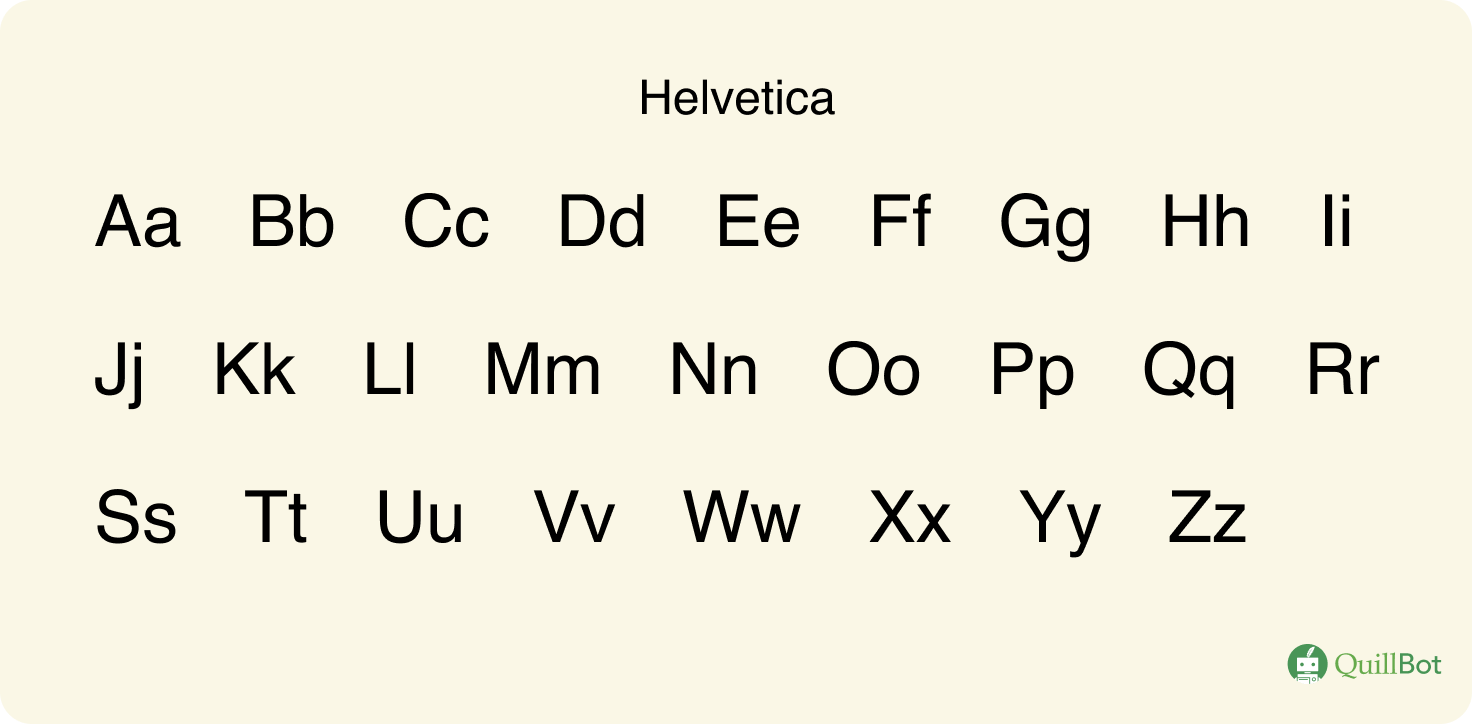
Helvetica | Une police intemporelle
Que ce soit sur le web, sur un panneau publicitaire, sur un bandeau télévisuel ou dans un magazine, le choix d’une police de caractère n’est jamais le fruit du hasard.
Loin de relever de la simple coquetterie ou du détail, une typographie peut, selon ses caractéristiques visuelles et l’ambiance qu’elle dégage, influencer considérablement la lisibilité et l’accessibilité d’un message, et même appuyer la ligne éditoriale d’une marque.
De polices, il en existe de toutes sortes : fines ou épaisses, fantaisistes ou classiques, rondes ou linéaires… L’offre, en vérité, est aujourd’hui pléthorique.
Parmi elles, on retrouve notamment les incontournables du genre, intégrés d’office sur tous les logiciels de traitement de texte par défaut, ou presque.
C’est à cette catégorie plus select qu’elle n’y paraît qu’Helvetica appartient.
- Année de création : 1957
- Pays de création : Suisse
- Créateur : Max Miedinger
- Type de police : Linéale
- Type d’empattement : Sans empattement (sans serif en anglais)
- Classification VoxAtypi : Linéale néo-grotesque
- Popularité : +++ (encore très populaire malgré son grand âge)
- Image véhiculée : Fonctionnelle, claire, universelle, mais aussi peu originale, voire austère.
- Point d’attention particulier : Espacement particulièrement serré (n’est donc pas adapté à tous les supports de lecture).
Helvetica, au même titre qu’Arial ou Times New Roman, figure parmi les polices les plus célèbres et influentes ; un incontournable dans l’univers du design graphique.
Le grand public, même lorsqu’il ne connaît pas son nom, a forcément déjà eu affaire à Helvetica.
Mais quels sont les secrets de cette popularité qui en fait toujours l’une des typographies les plus utilisées à l’échelle du globe actuellement ?
Comment est née la police Helvetica ?
La naissance d’Helvetica remonte à 1957.
On la doit à Max Miedinger, un spécialiste suisse de la création de caractères. Sous la houlette d’Eduard Hoffmann, celui-ci avait pour consigne de créer une police qui soit la plus neutre, pratique, rationnelle et universelle possible.
L’idée directrice était la suivante : cette nouvelle typographie devait laisser s’exprimer le texte en soi, sans orienter le lecteur quant à son contenu en raison de ses lignes et de son apparence.
Qu’à cela ne tienne : Miedinger s’est mis au travail, et Helvetica est née.
Et si votre cerveau fait directement le lien entre « Helvetica » et « helvétique », là encore, point de coïncidence : non contente d’assumer son héritage helvète, Helvetica va plus loin que cela ; elle le revendique, jusqu’à s’ériger en véritable symbole de la typographie suisse !
En effet, son premier nom était Neue Haas Grotesk, en référence à la Haas’sche Schriftgiesserei, qui n’est autre que la fonderie suisse qui l’a produite, et à la police d’écriture dont elle descend, Akzidenz-Grotesk.
Ce n’est qu’en 1960 que son nom change pour Helvetica, pour des raisons pratiques relatives à sa récente diffusion à l’international.
Caractéristiques de la police Helvetica
Helvetica est une police de caractère dite linéale, ou sans empattement.
Cette distinction s’opère selon un critère visuel immédiatement reconnaissable.
- Les polices serif (avec empattement en français) possèdent de petits « pieds », crochets ou traits décoratifs aux extrémités de leurs caractères.
Elles renvoient à un design classique, sérieux, et confèrent à la communication un caractère institutionnel symbolique d’une certaine autorité.
Elles sont aussi très utilisées dans l’édition et la presse écrite, car jugées plus confortables pour la lecture de textes sur le long court.
Exemples de polices avec empattement : Times New Roman, Baskerville, Garamond, Palatino Linotype…
- Les polices sans serif ne possèdent pas d’empattements ; leurs lignes sont droites et nettes.
Leur aspect est moderne et minimaliste ; leur design épuré, mais accessible.
On les utilise volontiers sur le web en raison de leur lisibilité optimisée pour les écrans et de leur côté « percutant ».
Exemples de polices sans empattement : Arial, Calibri, Tahoma, Futura, Roboto, Open Sans…
Conformément au cahier des charges qui incombait à son créateur, Helvetica a été sciemment conçue pour se faire invisible.
Son concept est simple : ne pas attirer l’attention sur elle-même, mais servir le message avec clarté, neutralité et efficacité, en parfait accord avec le style typographique suisse.
En outre, Helvetica offre une excellente lisibilité dans toutes les tailles, ainsi qu’un espace régulier et homogène.
Elle possède plusieurs variantes selon les différentes graisses, obliques et largeurs qu’elle peut prendre :
- Helvetica Bold,
- Helvetica Bold Oblique,
- Helvetica Light,
- Helvetica Light Oblique,
- Helvetica Medium,
- Helvetica Oblique,
- Helvetica Regular…
Aujourd’hui, c’est sa refonte de 1983, Helvetica Neue, qui est la plus utilisée.
Citons également Helvetica Now, une version d’Helvetica plus moderne encore, optimisée pour les écrans et l’impression à grande échelle.
Police Helvetica : quels usages ?
Si d’aucuns peuvent reprocher à Helvetica son manque de singularité et de caractère (sans mauvais jeu de mots…), elle n’en reste pas moins prisée par les graphistes, surtout lorsqu’il s’agit de concevoir :
- des interfaces numériques accessibles,
- des logos de marque percutants,
- des signalétiques,
- des publicités,
- des supports d’information ou des panneaux d’affichage,
- des panneaux d’information et d’orientation dédiés aux transports en commun, dans les gares, les stations souterraines et les aéroports (par exemple, le métro de New York a longtemps écrit le nom de ses stations avec Helvetica)…
En vérité, Helvetica est un choix sûr pour tout contenu privilégiant avant tout la lisibilité, l’efficacité et la cohérence.
Elle fut leur police emblématique jusqu’en 2015, date à partir de laquelle elle a été remplacée par San Francisco, une police assez proche en termes de morphologie, mais aux lignes plus fines et mieux adaptée aux définitions d’écran les plus nettes.
Bonus : les polices proches d’Helvetica
Helvetica, en tant que légende emblématique du monde de la typographie, a inspiré de nombreux créateurs en herbe par la suite.
Ainsi, parmi ses polices les plus proches en termes de morphologie, on retrouve :
- Arial,
- Avshalom MF,
- Nimbus Sans,
- Roboto,
- Open Sans,
- Segoe UI,
- Univers…
Voilà de quoi varier les plaisirs…